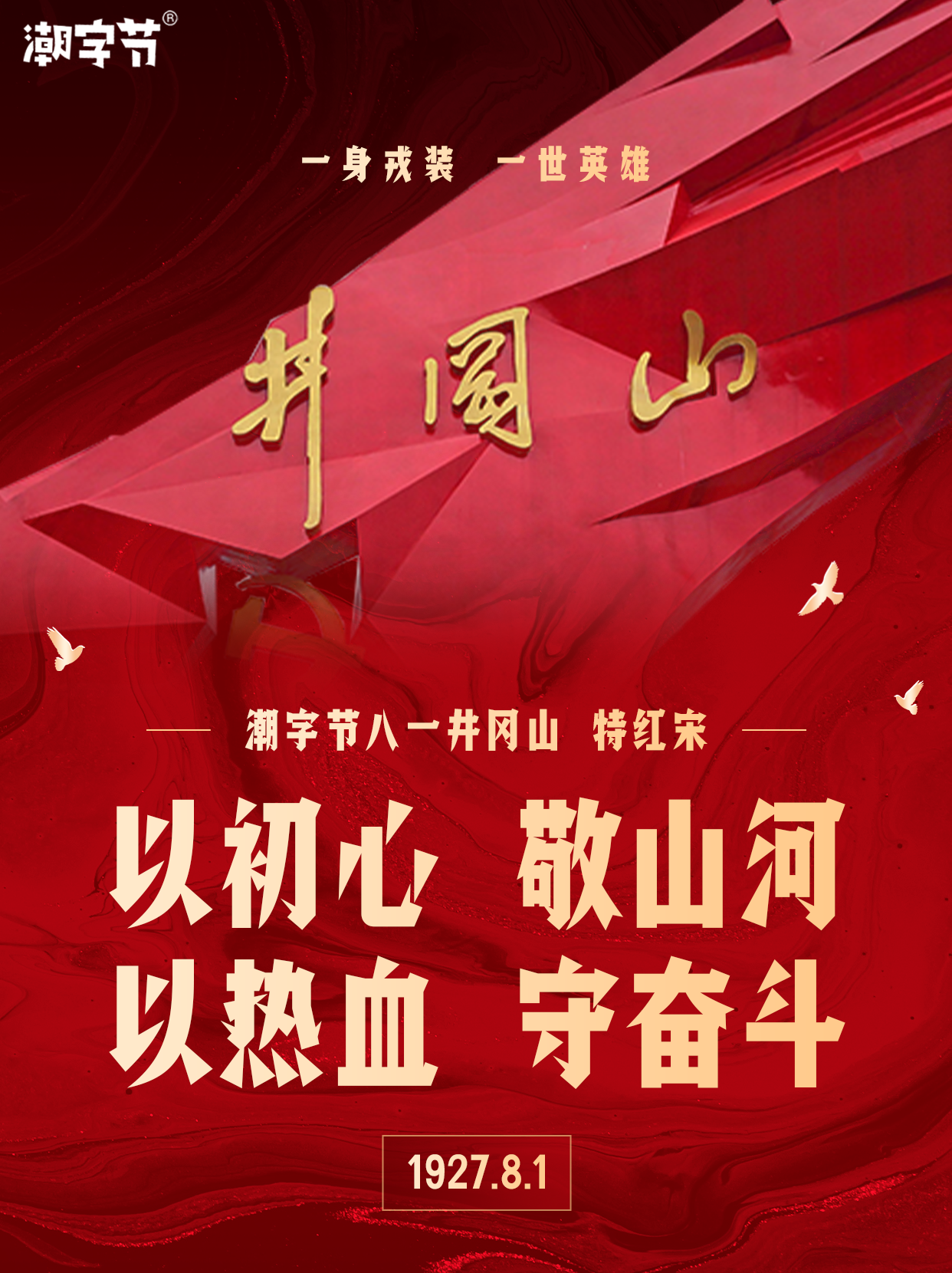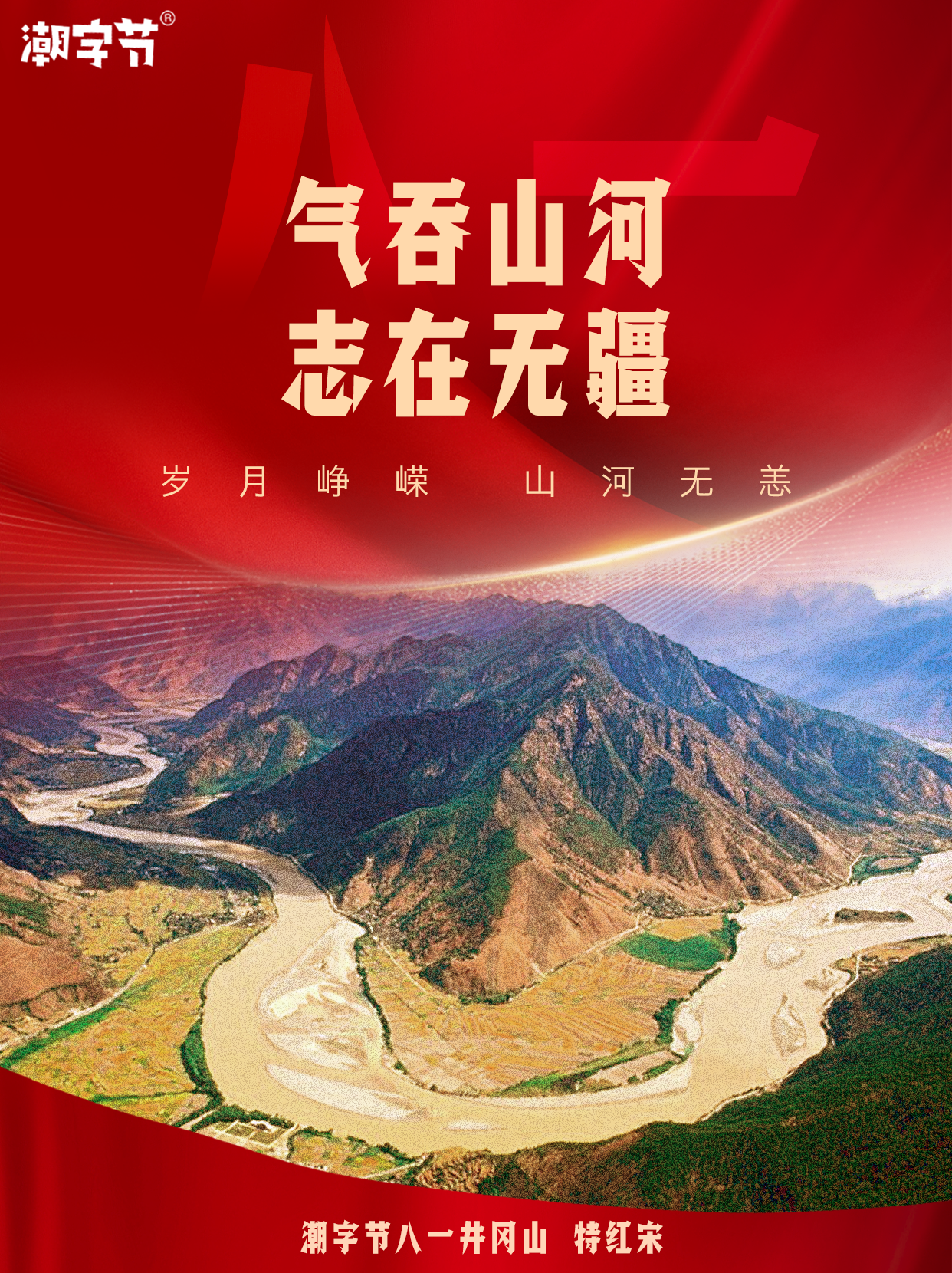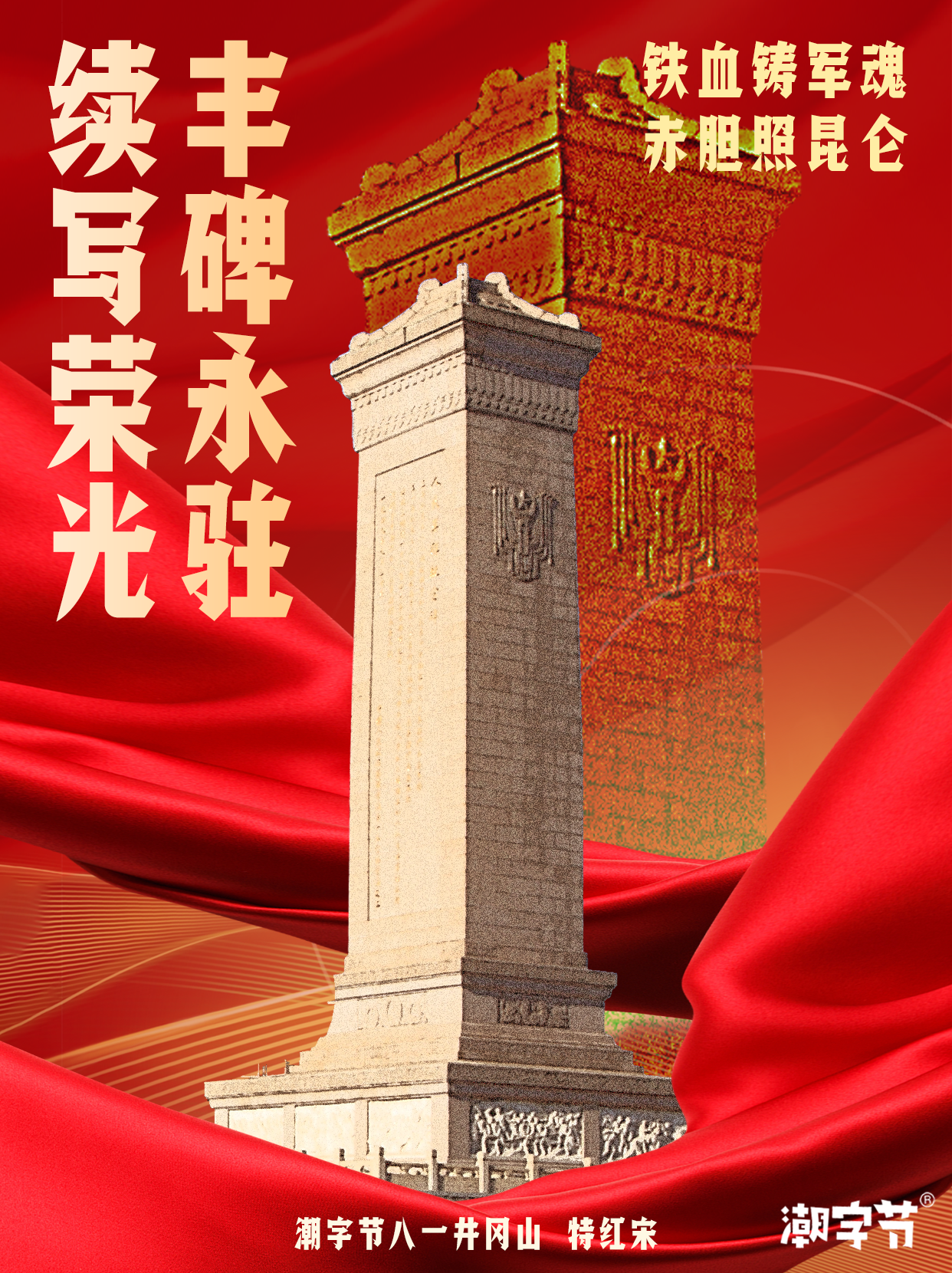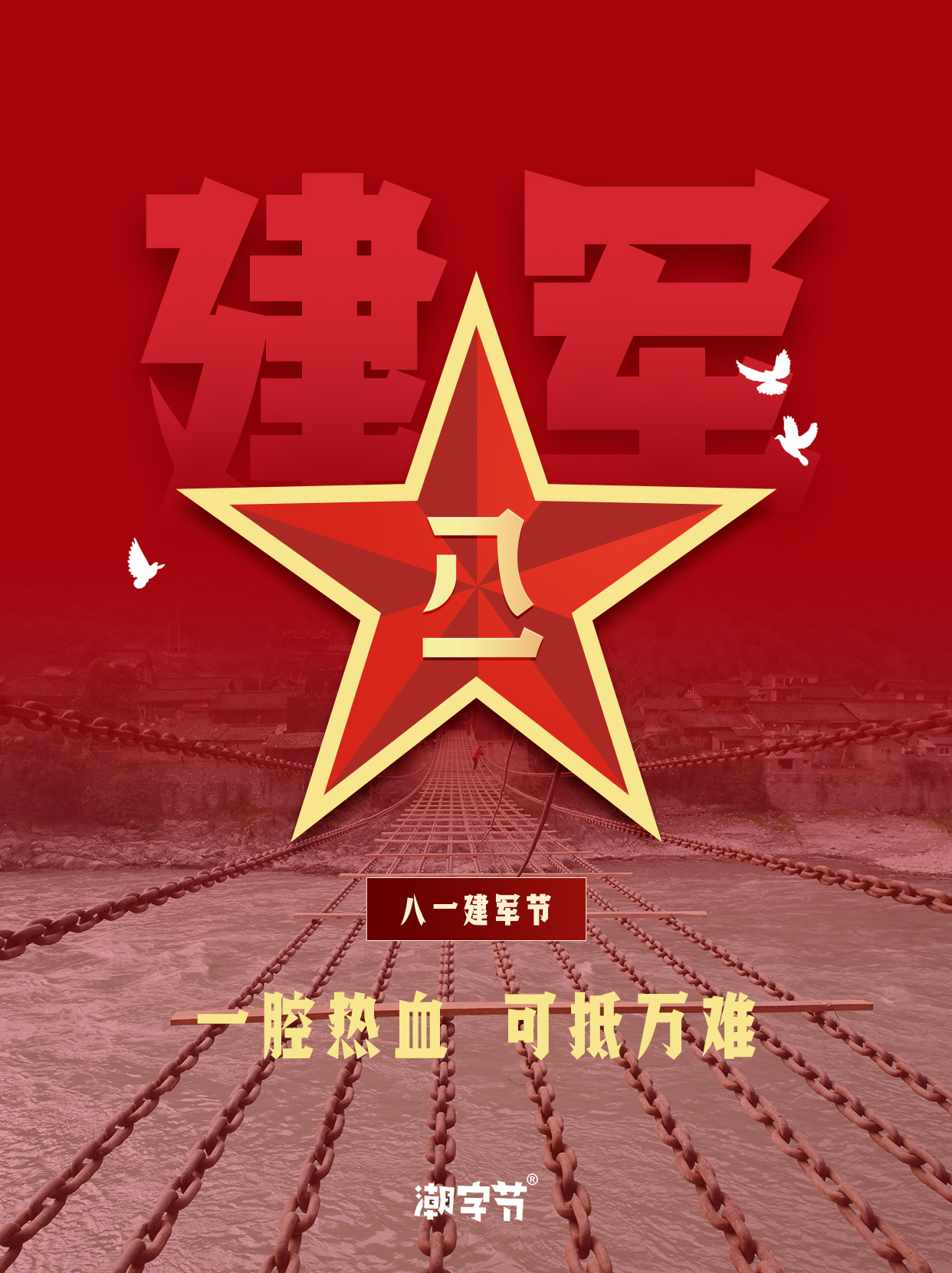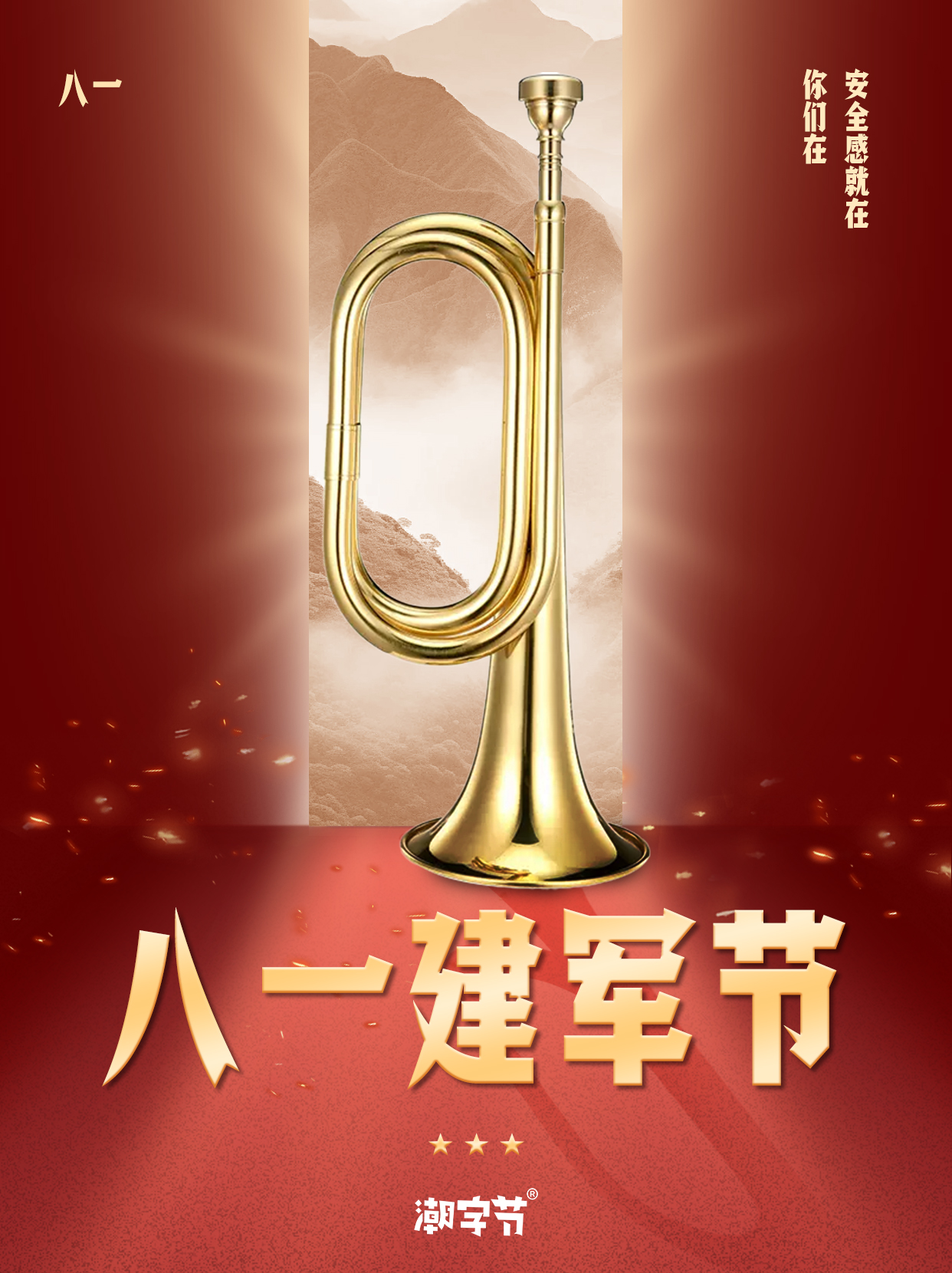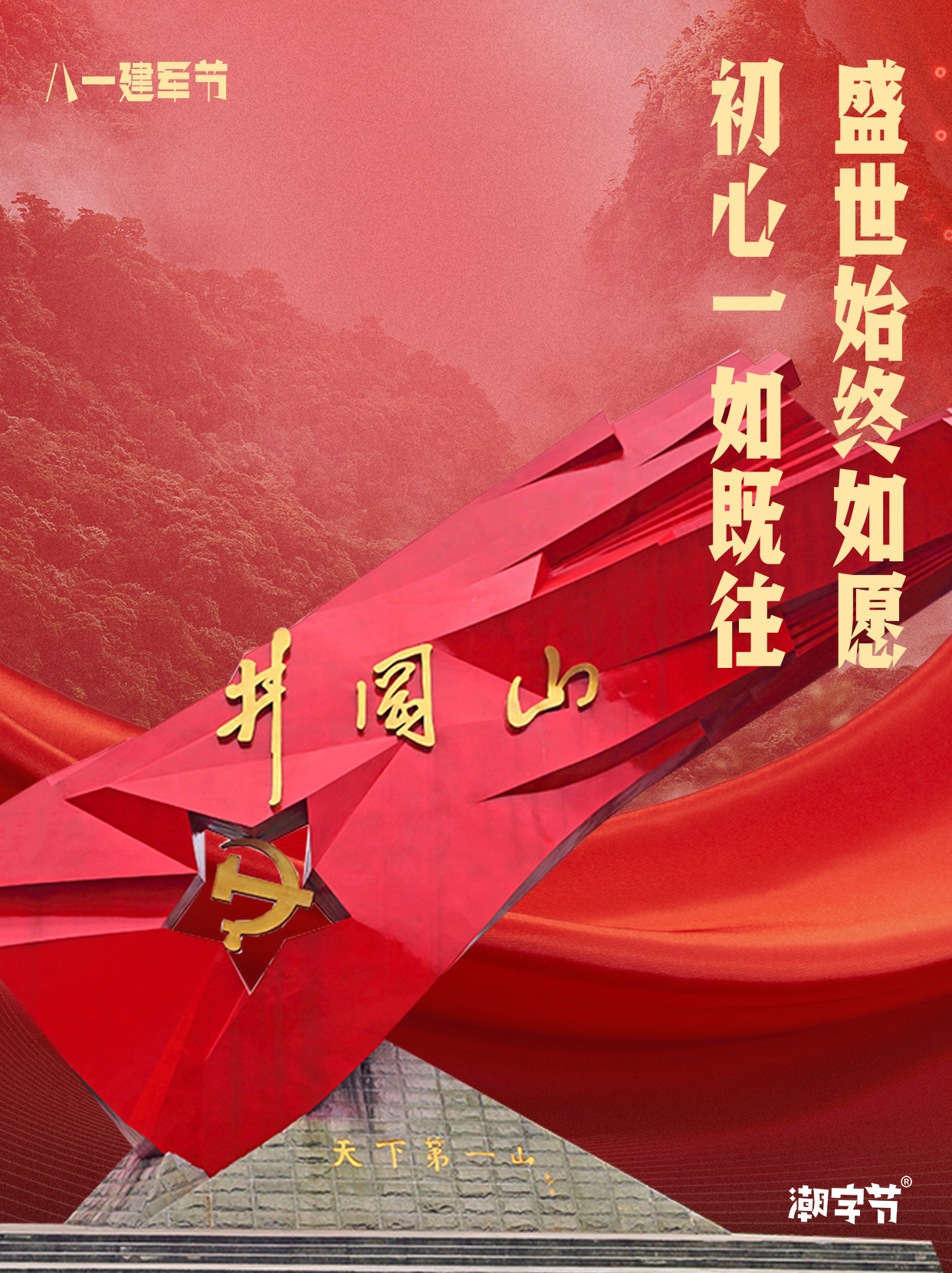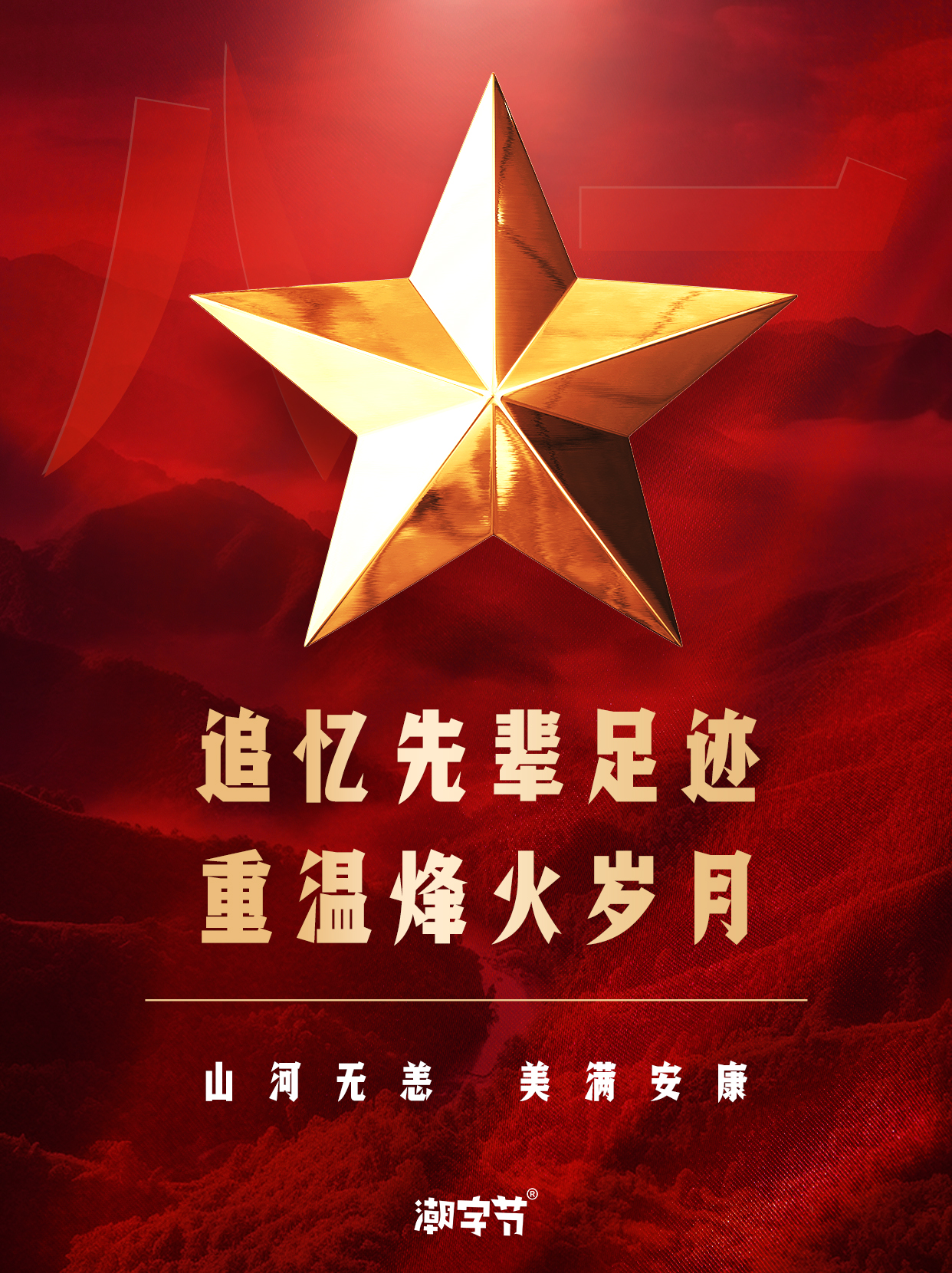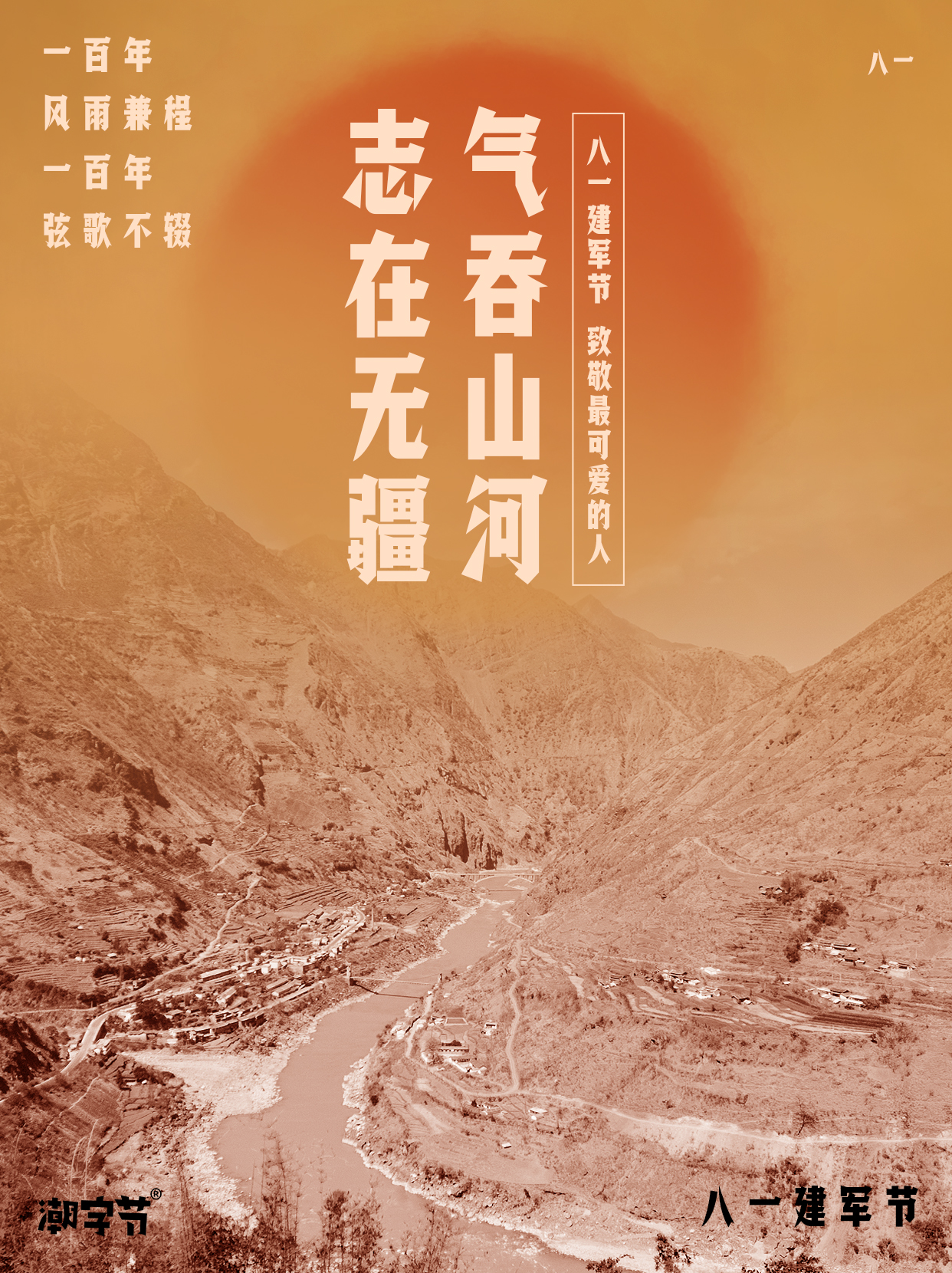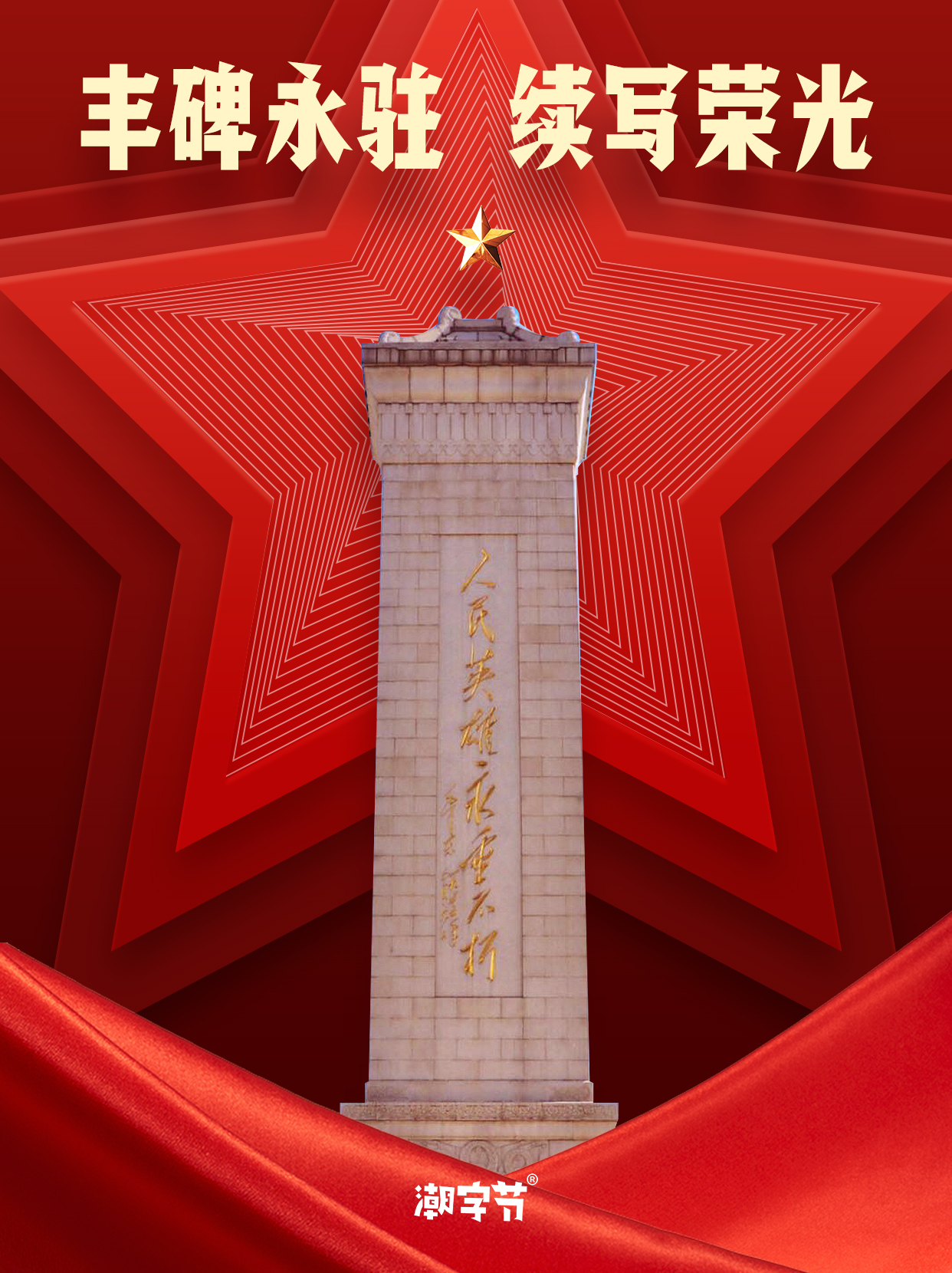
该字体是一款复古式字形与现代化宋体完美结合于一体的美术宋体。较瘦长,粗细均匀,布白合理。
横笔画末端和折笔处加入斜角装饰特点,撇、点笔画曲线坚毅锐利,不同位置和空间的撇笔画处理方式灵活,钩笔画收笔处折笔带尖,融入宋体形态特点。“口”结构等根据位置出头形态兼备斜切与平切,处理简约,笔画简洁,呈现一种极冷静、极尖利的刚毅之美。